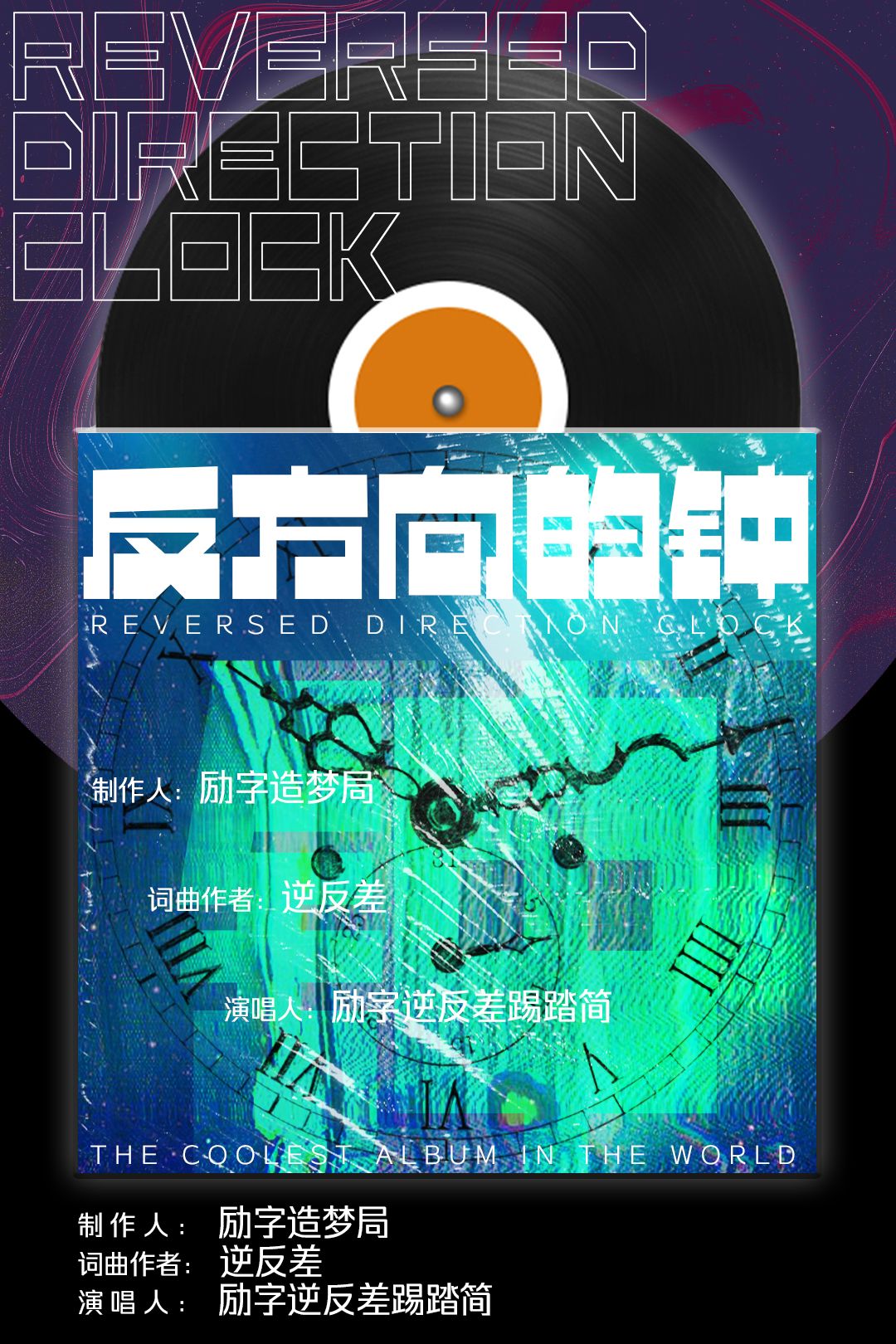
迷幻反叛的潮流风格字体——励字逆反差踢踏简
喜欢跳舞吗?迷幻的电音派对,七彩的霓虹晃动,一款特立独行的潮流酸性字体——励字逆反差踢踏简满足品牌的多元个性需求。
酸性设计其实一种挑战传统美感的设计风格,脱身于地下音乐而自带反叛精神。而酸性设计的字体也会呈现出哥特式的装饰感,夸张变形,且十分尖锐,通常会配合金属效果。
励字逆反差踢踏简,字型规整方正,笔画的粗细对比明显。是一款横平竖直、顶部底部笔画厚重、中间笔画极细的逆反差直线字体。起笔收笔采用平直的特点,中宫宽阔、重心平稳、布白均匀。笔画摒弃繁琐特点,转折处均以直角的处理方式。顶部底部笔画灰度极度夸张。点笔画根据空间有多种表达方式、灵活多变。笔画对称、镜像的处理方式使得结构更为工整。